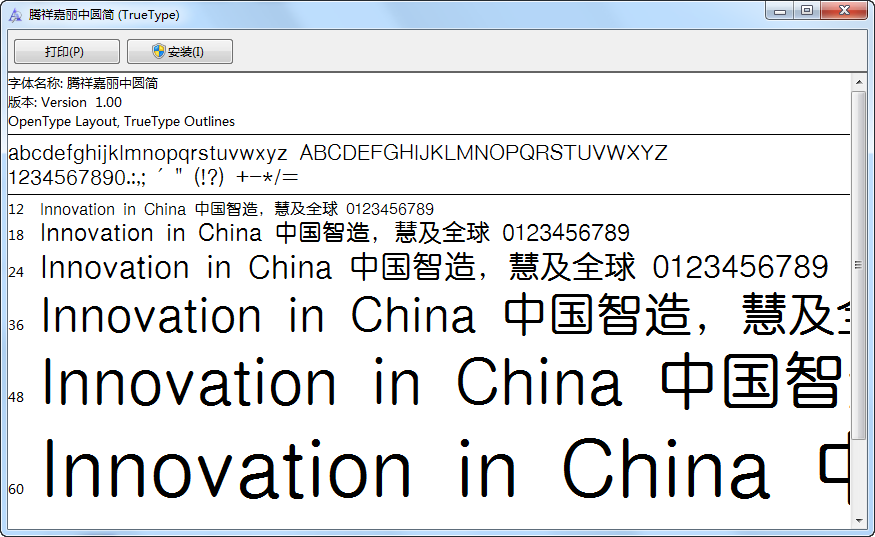
騰祥嘉麗中圓簡字體是一款可用于出版印刷、包裝設(shè)計、 屏幕顯示、廣告設(shè)計、網(wǎng)頁設(shè)計等多個不同領(lǐng)域使用的中文藝術(shù)字體,這款字體看上去十分美觀,有需要的用戶趕快來本站免費下載體驗吧!
騰祥嘉麗中圓簡是騰祥嘉麗圓體系列字庫的中圓字體。其中每個漢字都經(jīng)過精心設(shè)計,筆畫柔美光潔、粗細(xì)均勻、結(jié)構(gòu)美觀。每個字的圓角、圓頭、勾形都極光潔、風(fēng)格統(tǒng)一 字形放大不變形,縮小顯示清晰,整款字庫有不同的顯示和打印效果,筆型嚴(yán)謹(jǐn)規(guī) 范,適用于正文排版。